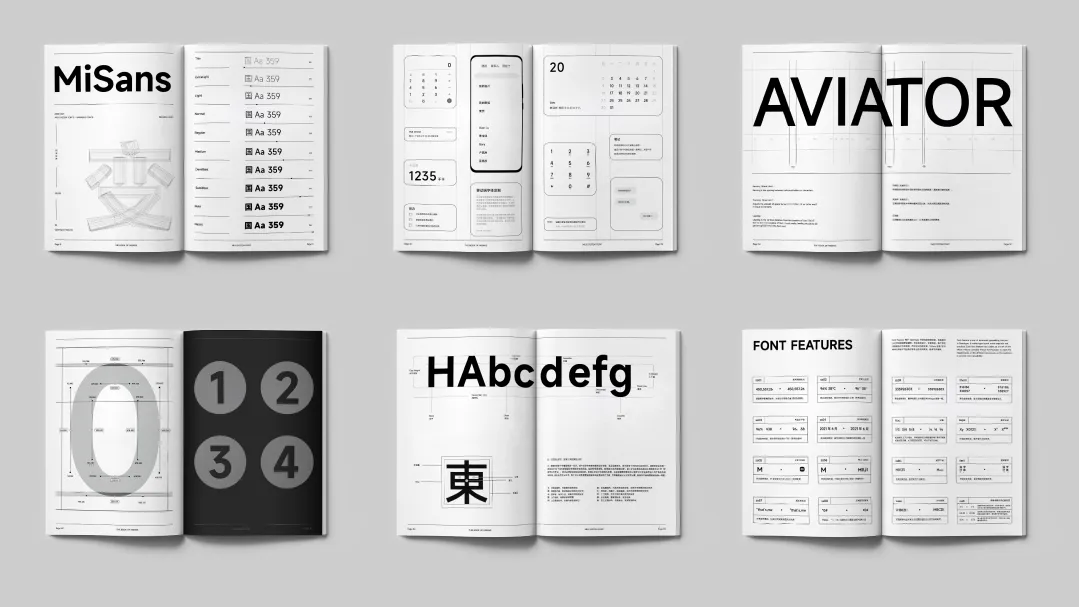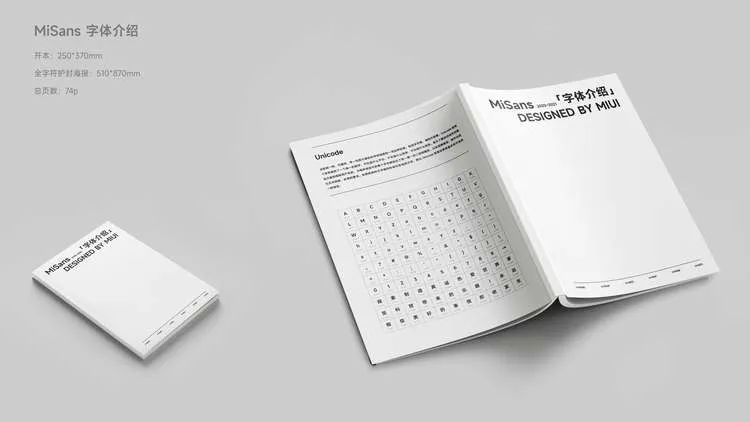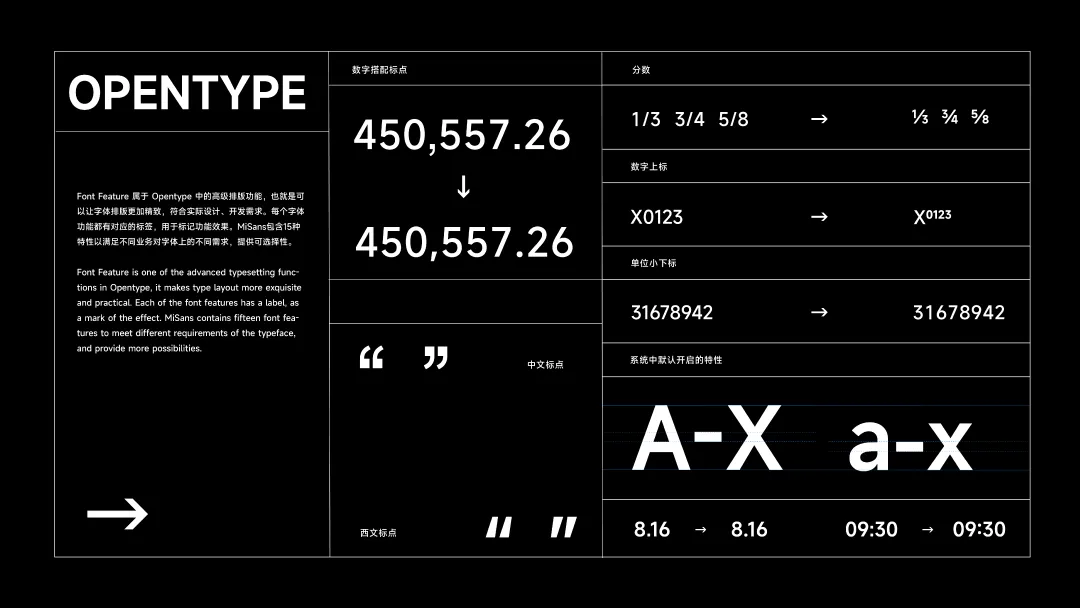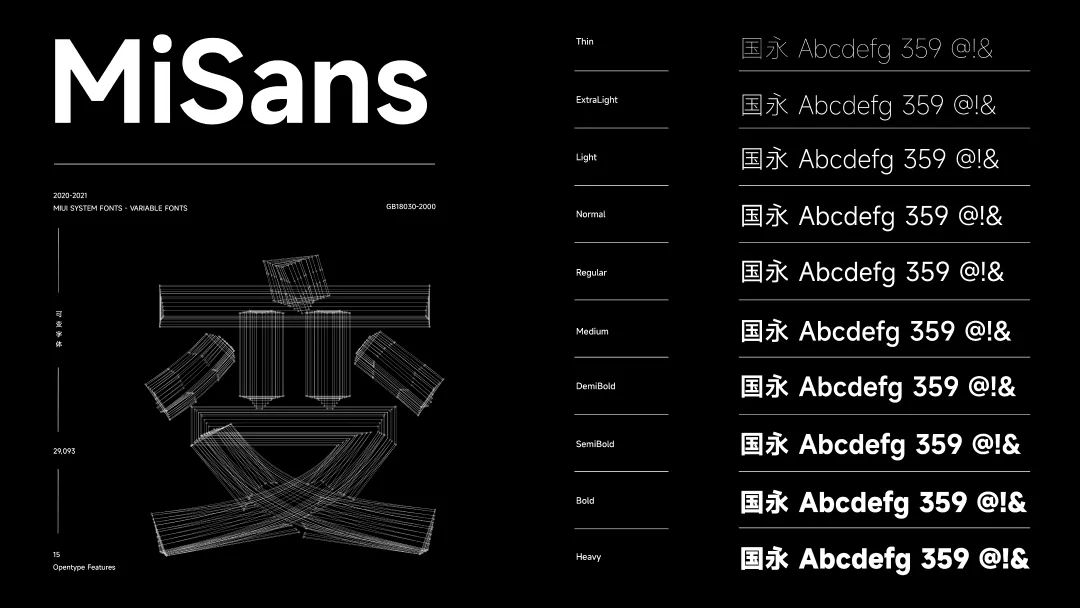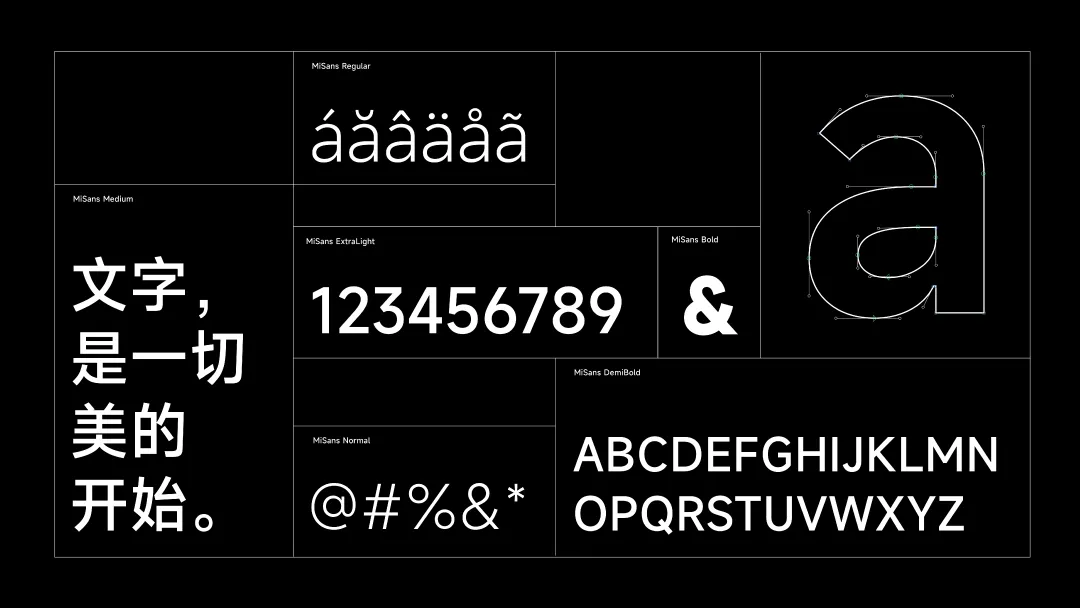
MiSans 是小米公司联合汉仪字库推出的一款可变无衬线字体,2021 年 12 月随 MIUI 13 系统发布且宣布全球免费商用。
MiSans 笔型平直有力,线条简洁明快,提供 10 个固定字重(Thin、Light、Regular至Heavy),支持多种语言,包含 29093 个字符。同时还内置 15+ OpenType 特性,可根据特定需求来选择不同形态的字符,例如某些标点符号可以根据周围字母的形态自动调整至合适的位置等。
MiSans 和 OPPO Sans、HarmonyOS Sans 等同为手机厂商定制的免费无衬线字体,但 MiSans 支持可变字体,可以适配手机系统 UI、APP 界面、网页正文 / 标题、PPT 演示、海报、电商物料等多种场景;尤其适合屏幕长文阅读与多端视觉统一的项目。